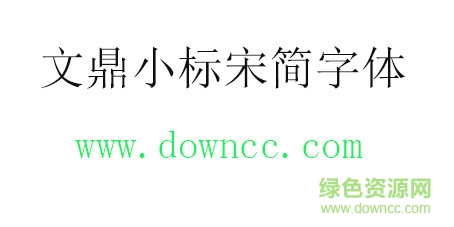
文鼎小標(biāo)宋簡是一款粗細(xì)分明的簡宋體,橫略細(xì),豎略錯,結(jié)構(gòu)清晰,并且支持win10系統(tǒng)使用,讓你辦公或者進(jìn)行其它書面描繪的工作中能夠多一項(xiàng)字體排版的選擇,也能充分展現(xiàn)出自己的個性哦,有需要的朋友,趕快下載體驗(yàn)吧!